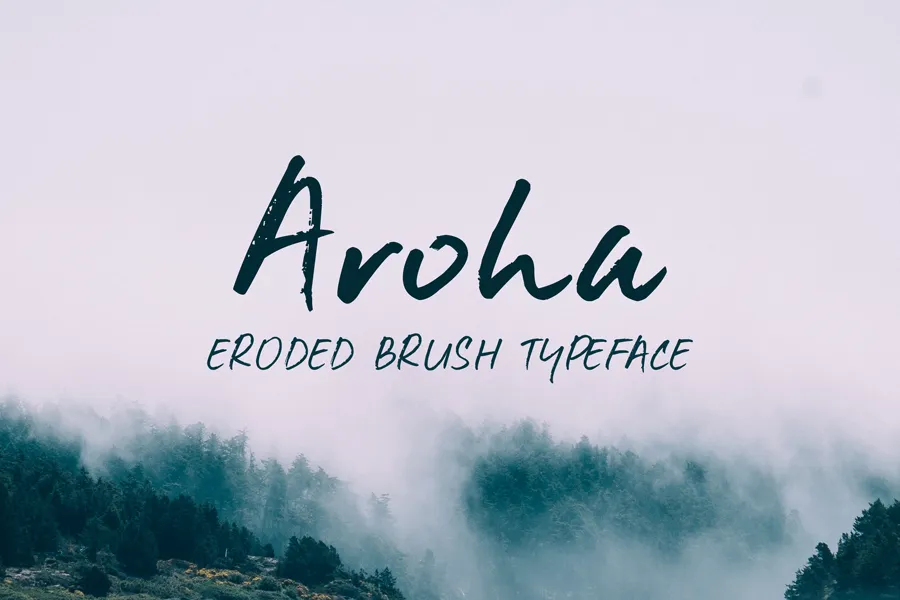
Aroha Brush Font é uma tipografia feita a partir do estilo de tração manual de um pincel, que evoluiu através dos erosions naturais das superfícies. Esta tipografia brush-lettering é perfeitamente imperfeita e traz um toque pessoal aos projetos gráficos. Seus traços definidos e seu formato livre fazem dele uma escolha ideal para aplicações de exibição e cabeçalhos, destacando-se em designs que buscam personalidade e autenticidade. O designer Hamilton criou Aroha Brush Font pensando em oferecer um resultado natural e único, perfeito para aqueles que valorizam o cuidado e a arte nas suas criações digitais.